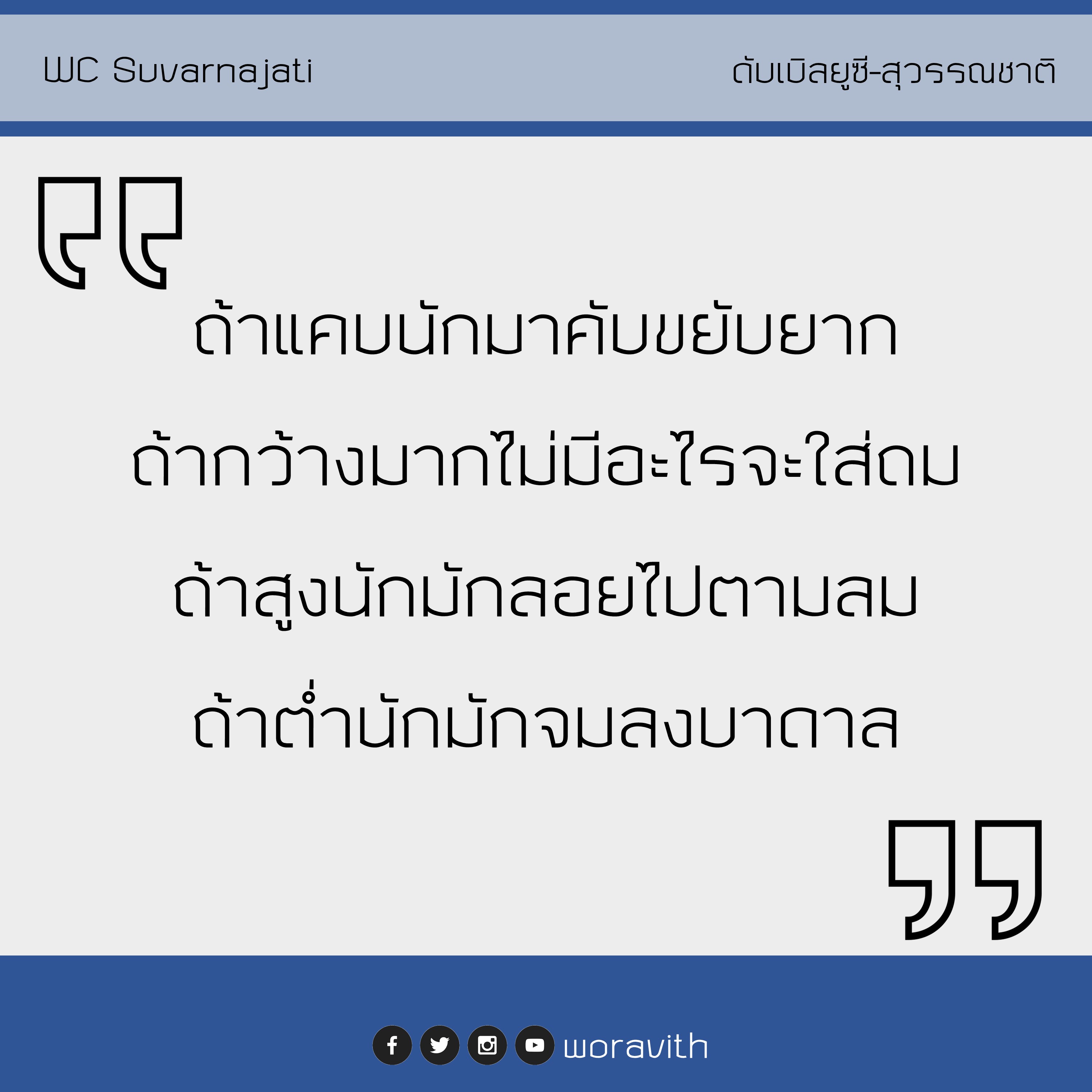
WC Suvarnajati
ชื่อฟอนต์ : ดับเบิลยูซี สุวรรณชาติ
Font Name : WC Suvarnajati
ผู้สร้างสรรค์ : วรวิทย์ จันทร์สุวรรณ
Creator : Woravith Chansuvarn
จำนวนน้ำหนัก : 2 (Regular แล Light)
แนวคิด : ฟอนต์สุวรรณชาติพัฒนาจากรูปวงรี ผสมผสานกับแนวเส้นตรง แสดงความเข้มแข็ง แต่มีส่วนโค้งให้อารมณ์อ่อนโยน